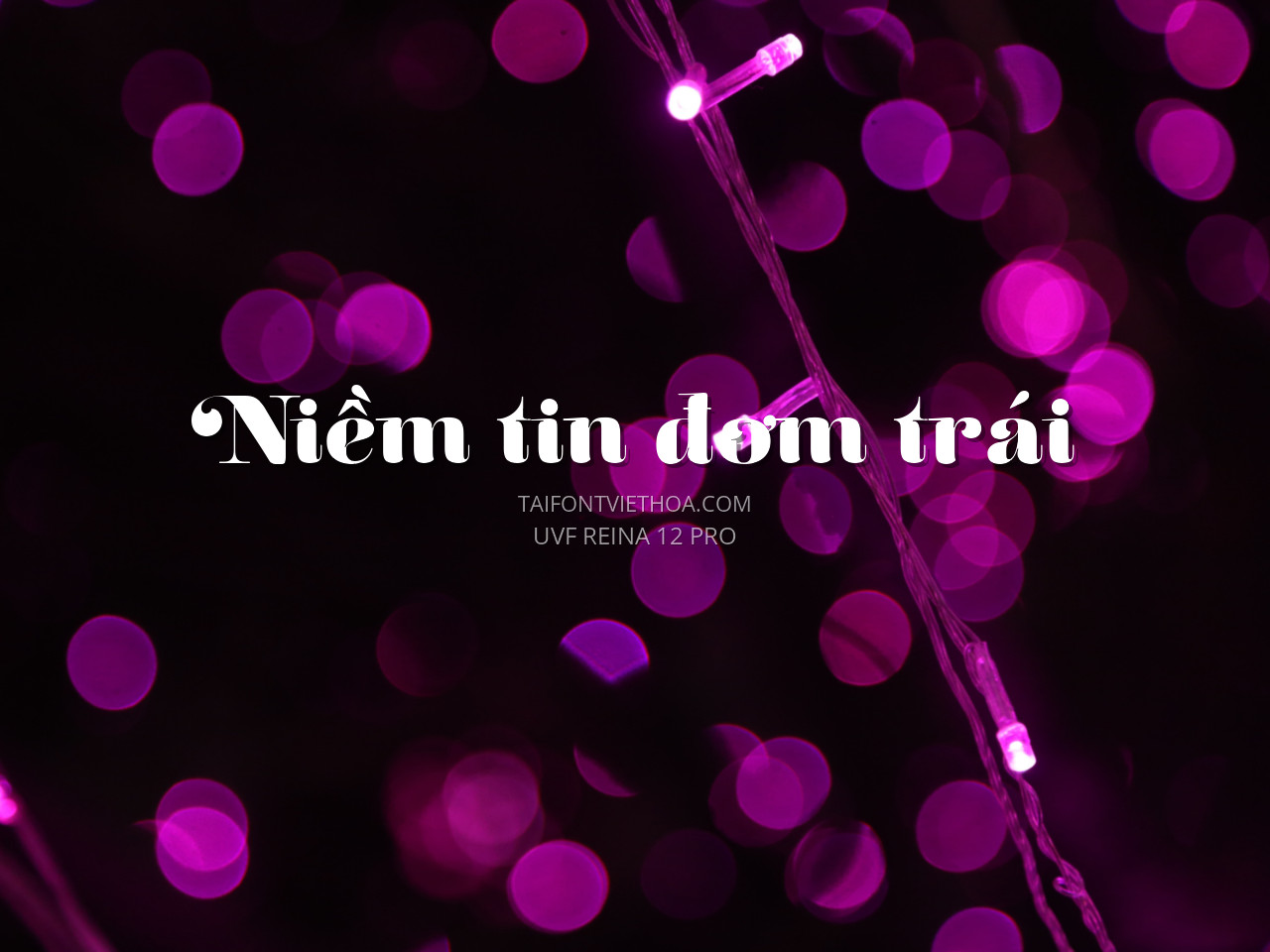
Font việt hóa UVF Reina 12 Pro
Giới thiệu về font UVF Reina 12 Pro
UVF Reina 12 Pro là một kiểu chữ serif tinh xảo, được phát triển theo phong cách calligraphic hiện đại với ảnh hưởng mạnh từ các yếu tố thời trang và nghệ thuật cao cấp. Font gốc “Reina” do Lián Types phát triển, lần đầu ra mắt vào khoảng năm 2012, nhanh chóng trở thành biểu tượng trong các thiết kế thời trang, đặc biệt được ưa chuộng trong các dự án branding, bìa tạp chí và mỹ phẩm cao cấp. Reina hỗ trợ hơn 200 ngôn ngữ, bao gồm cả tiếng Việt và các bộ ký tự Latinh mở rộng, Cyrillic,…
Đặc điểm thiết kế và khả năng ứng dụng của UVF Reina 12 Pro
Reina 12 Pro nổi bật nhờ độ tương phản cực cao giữa nét dày và mảnh – một đặc điểm của các font Didone, nhưng được cách điệu mềm mại với các đường cong mượt mà và đầu chữ có đuôi móc độc đáo. Font được tích hợp nhiều ligature cùng ký tự stylistic alternates, tạo sự biến hóa tối đa cho từng dòng chữ, phù hợp cả với tiêu đề và nội dung.
UVF Reina 12 Pro đặc biệt thích hợp trong các ứng dụng yêu cầu tính nghệ thuật và sang trọng như: thiết kế logo thời trang, bao bì mỹ phẩm, tiêu đề tạp chí, thư mời cao cấp, thiết kế bìa sách hoặc sản phẩm đồ họa sáng tạo. Ngành nghề phù hợp bao gồm: thời trang, mỹ phẩm, sự kiện, truyền thông cao cấp và quảng cáo nghệ thuật.